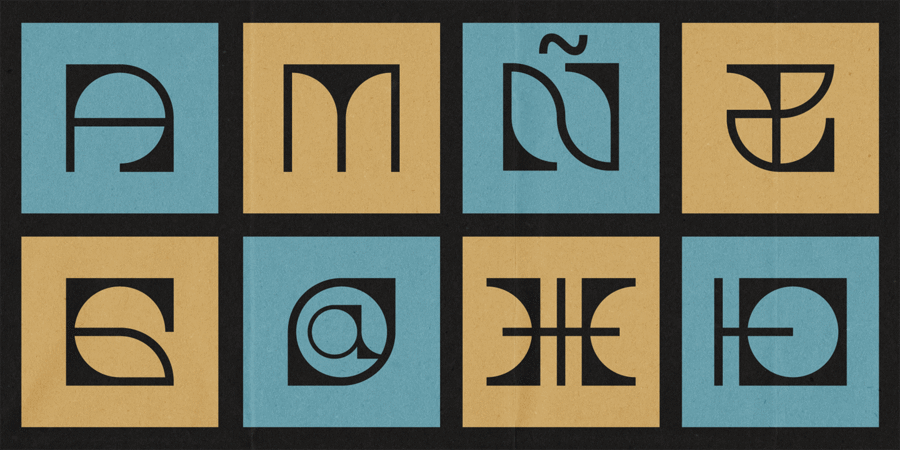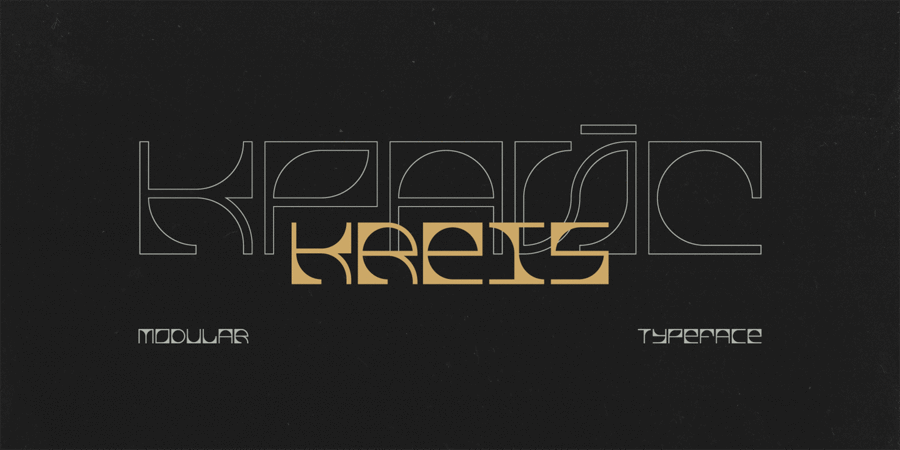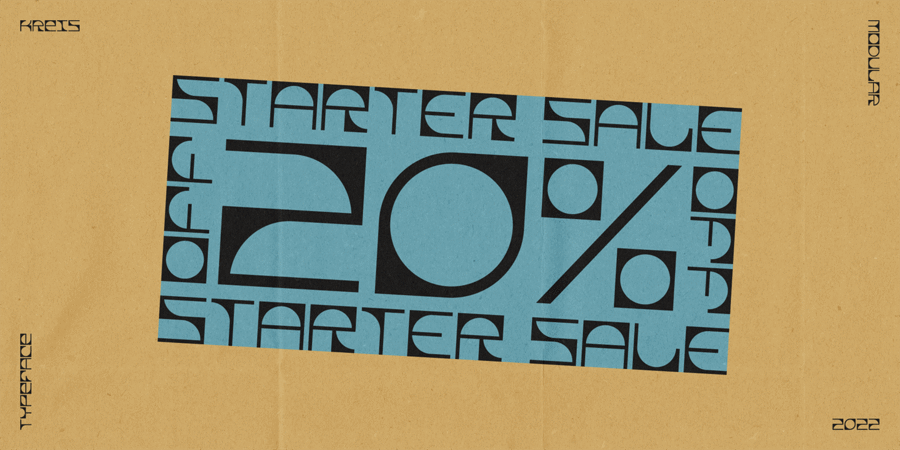
KREIS (КРАЙС). Модульний шрифт
KREIS – справжній метамодерніст, створений Катериною Королевцевою. Це модульний акцидентний шрифт із сучасним різким характером, натхненний формою олдскульного CD-диска. Він складається з трьох простих модулів, які походять з квадрата та кола. Kreis – німецьке слово, що означає коло.
KREIS має багато альтернатив, підтримує розширену латиницю та кирилицю. Шрифт найкраще пасує для заголовків, логотипів та сильних духом месседжів.
Шрифт розробила Катерина Королевцева у 2022 році.
Особливості сімейства шрифтів KREISХіт десятиліття:
Хіт 1930-х Хіт 1960-х Хіт 1970-х Хіт 1980-х KREIS підтримує 83 мовиУкраїнська, Англійська, Німецька, Польська, Португальська, Іспанська, Французька, Російська, Чеська, Голландська, Італійська, Шведська, Турецька, Фінська, Білоруська, Сербська, Болгарська, Естонська, Литовська, Албанська, Африкаанс, Баскська, Бретонська, Валенсаска, Galician, Гельська (Шотландська), Данська, Індонезійська, Ірландська, Ісландська (Win), Каракалпацька, Каталонська, Норвезька, Окситанська, Ретороманська, Самі Лулі, Тсванська, Узбецька (Лат.), Фарерська, фризька, Чаморро, Естонська (Win), Південносаамська, Албанська (Win), Угорська, Верхньолужицька, Карельська, Латвійська (Mac), Литовська (Mac), Маорійські (Mac), Молдавська (Лат.), Нижньолужицька, Румунська (Win), Словацька, Словенська, Туркменська (Лат.), Хорватська (Win), Естонська (Mac), Курдська, Латишська, Маорійські, Руминська, Абазинська, Аварська, Агульська, Адигейська, Даргинську, Інгуську, Кабардино-Черкеська, Кабардинська, Карачаєво-Балкарська, Кумицька, Лакська, Лезгинська, Македонську, Мордовсько-Мокшанська, Мордовсько-Ерзянська, Ногайська, Рутульська, Табасаранська, Татська, Цахурська, Чеченська Функції сімейства шрифтів KREISЗастосування гарнітури у верстці:
Асоціації з сімейством шрифтів KREISОсобистість і характер гарнітури:
оригінальний, якісний, міський, точний, рівний, ритмічний, експериментальний, дивний, електронний, автоматичний, машинний, сталевий, гострий, різкий, чіткий, жорсткий, квадратний, архітектурний, креслярський, інженерний, урбаністичний, техногенний, матричний, індустріальний, холодний, твердий, футуристичний, помітний, яскравий, активний, динамічний